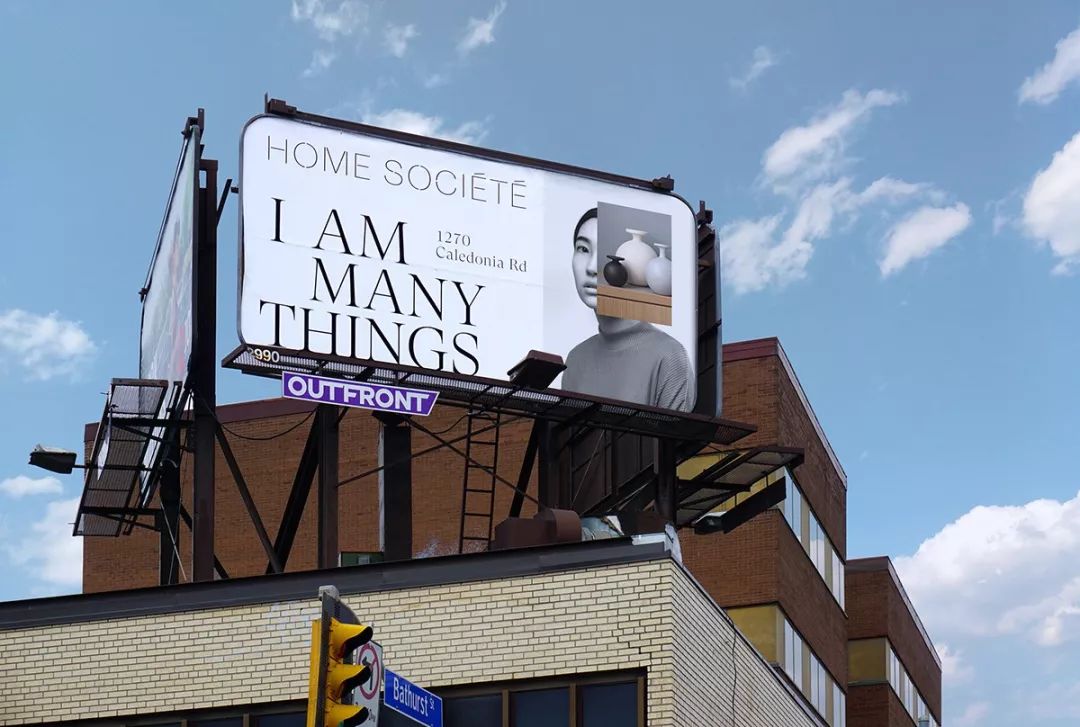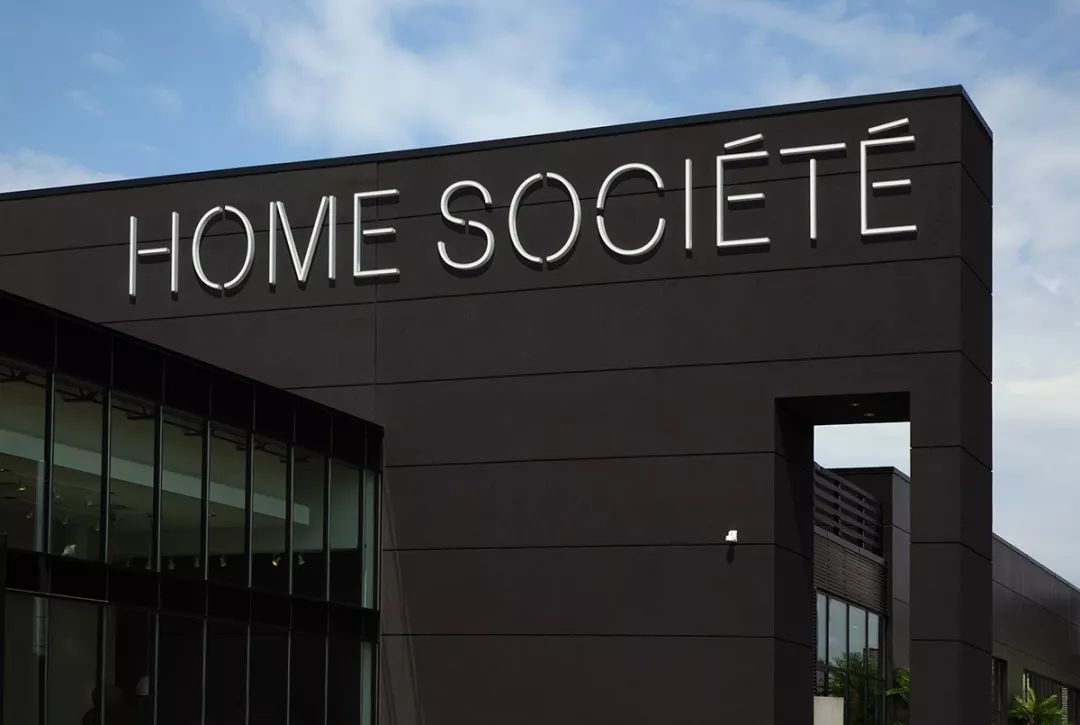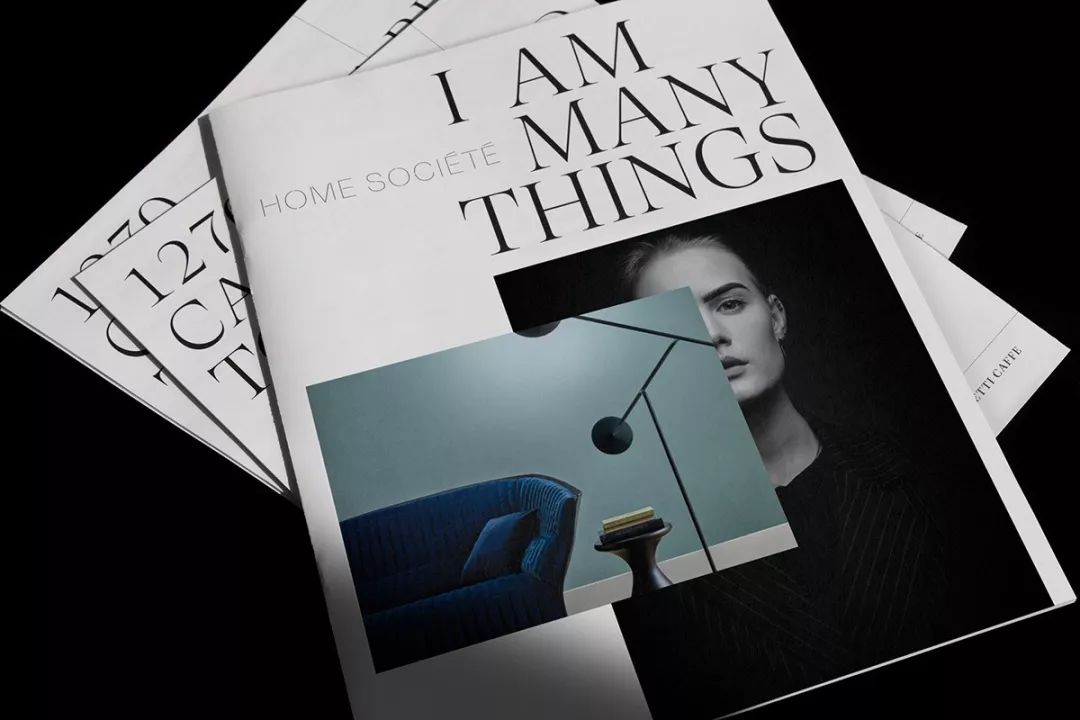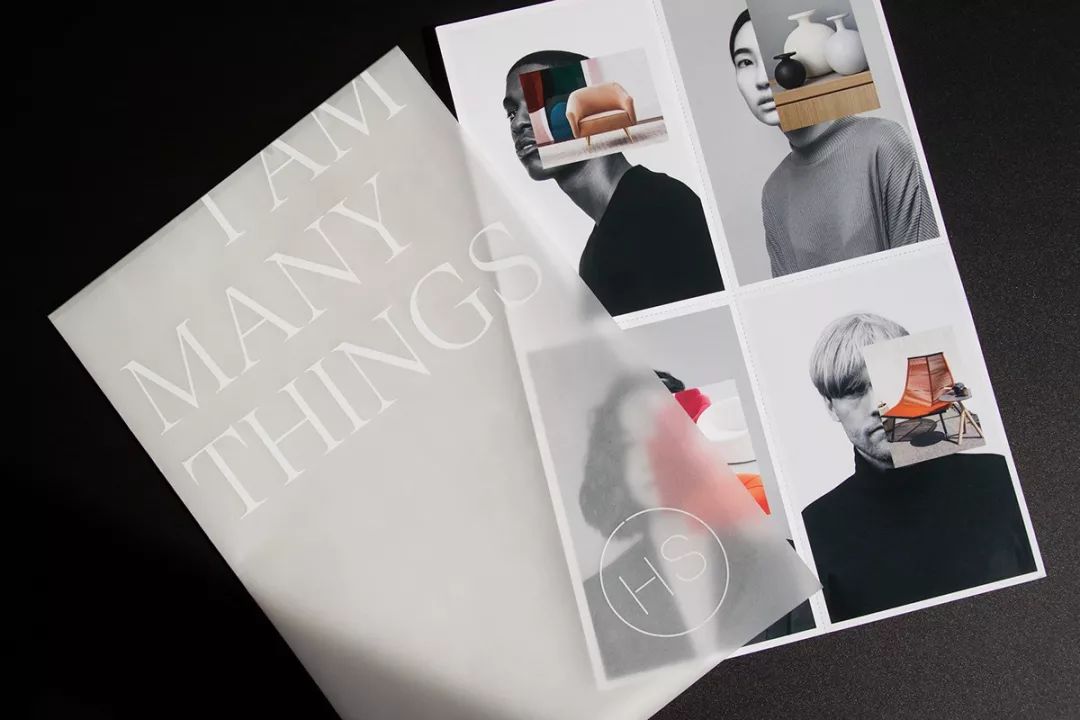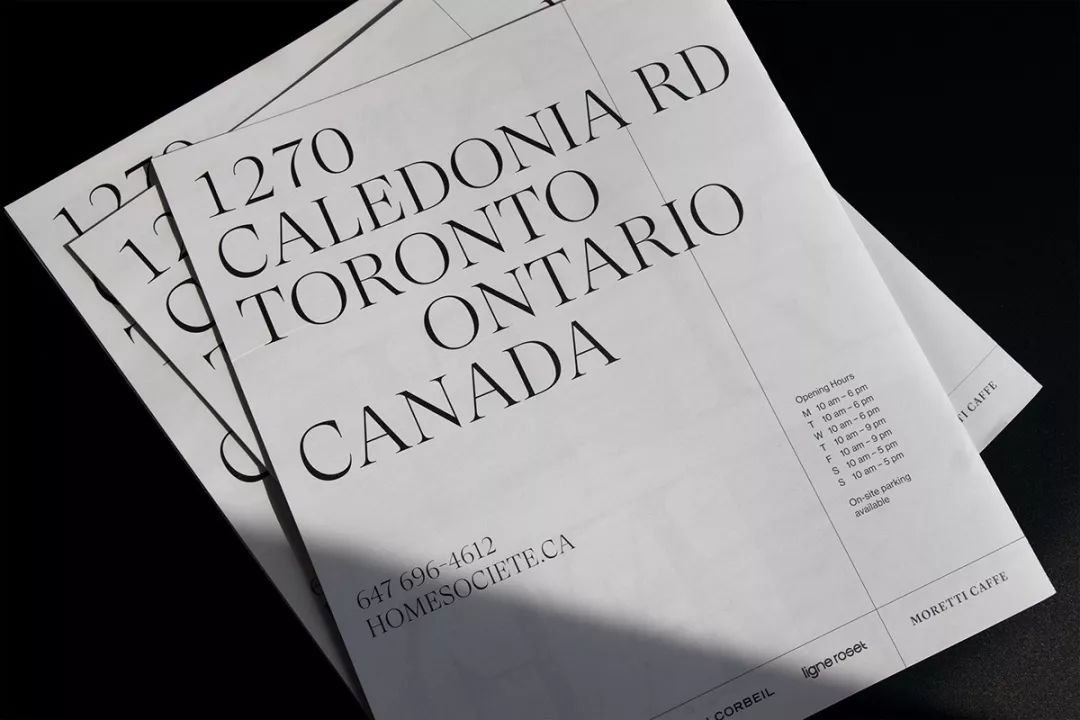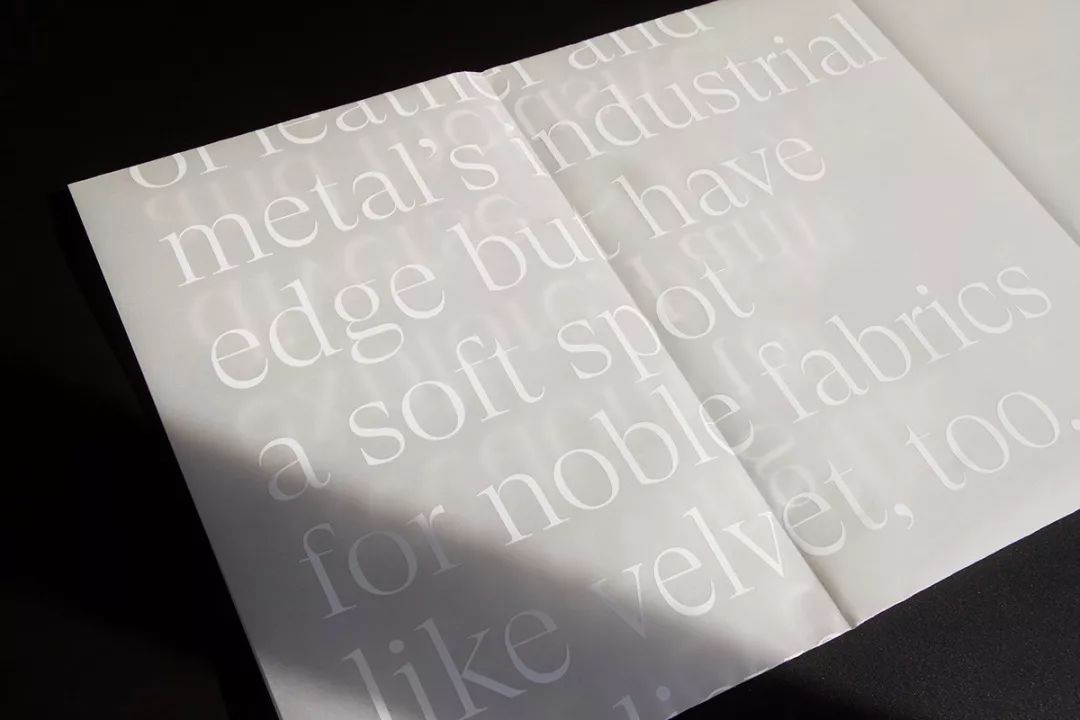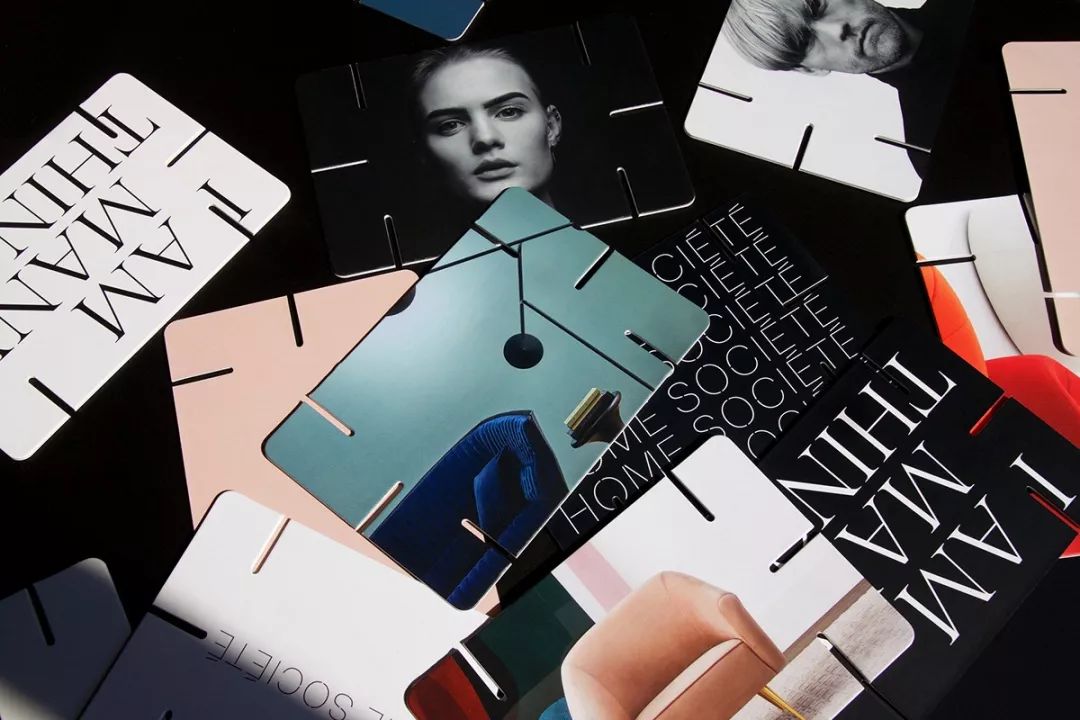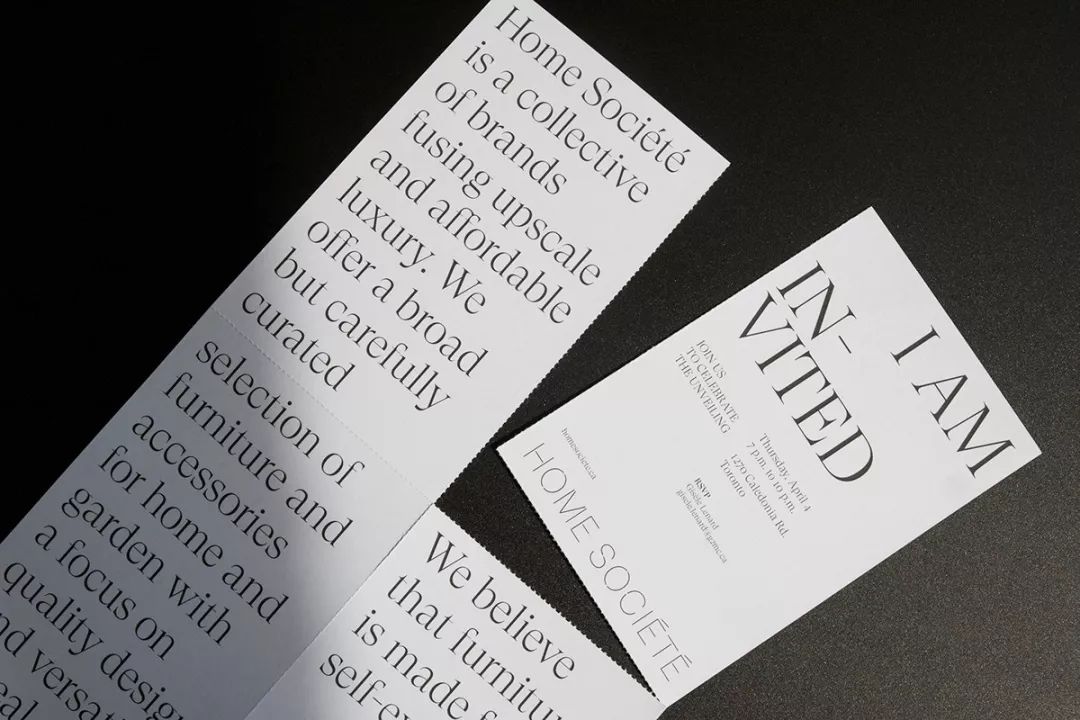
高级品牌的LOGO,怎么设计最有趣
Home Société是多伦多一家设计家俱集合店,专门销售高级家居及配套用品。Home Société的LOGO设计优雅精致,而一加上动态的效果,立刻变得有趣而充满活力,有趣一点的LOGO在高端品牌里是不多见的。
Home Société品牌形象来自Paprika广告公司,详细的创意人员名单参见文末。这套设计还获得了2019年度Communication Arts奖。